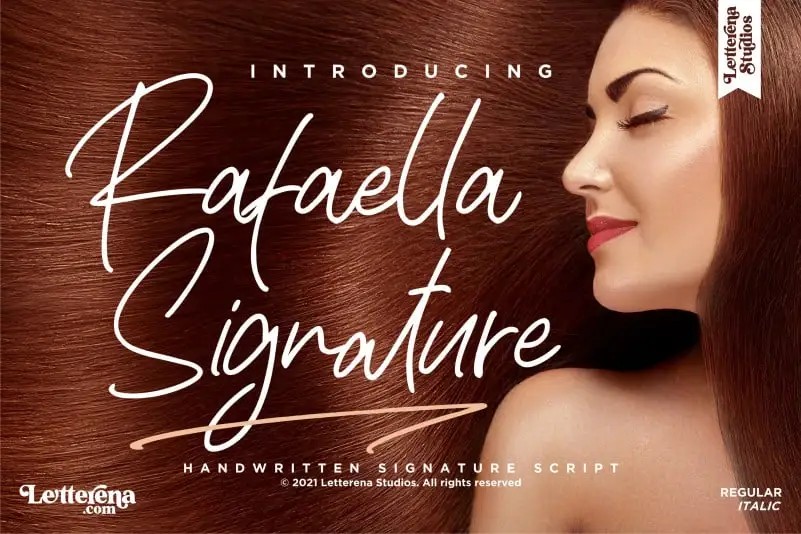
A Rafaella Signature Script Font é uma elegante escolha para aqueles que valorizam a sofisticação do handwritten com um toque romântico. Criada pela Letterenastudios, esta fonte de script retrata perfeitamente os desejos dos projetistas contemporâneos por uma mistura única entre elegância e personalidade. Suave e fluida, ela atende a uma ampla variedade de necessidades de design. Perfeita para criar identidades visuais memoráveis, desde logotipos até embalagens de produtos e materiais de decoração como posters, capas de livros ou cartões de presentes. O designer Letterenastudios entende que o charme da escrita livre desempenha um papel crucial em vários aspectos do design gráfico. É ideal para personalizar itens como mugs, etiquetas e embalagens de produtos, bem como criar materiais promocionais impecáveis. Esta fonte também se destaca pela sua versatilidade, adaptando-se perfeitamente tanto à arte digital quanto aos projetos tradicionais manuais. Seja um projeto para a web ou impressão em larga escala, Rafaella Signature Script Font oferece a oportunidade de adicionar um toque inconfundível e sofisticado às suas criações. Através de sua natureza romântica e elegante, este script atingirá o coração do seu público-alvo, criando uma conexão única entre o design visual e a mensagem que pretende transmitir. Enganche seus clientes com um toque autêntico e sofisticado, usando Rafaella Signature Script Font.